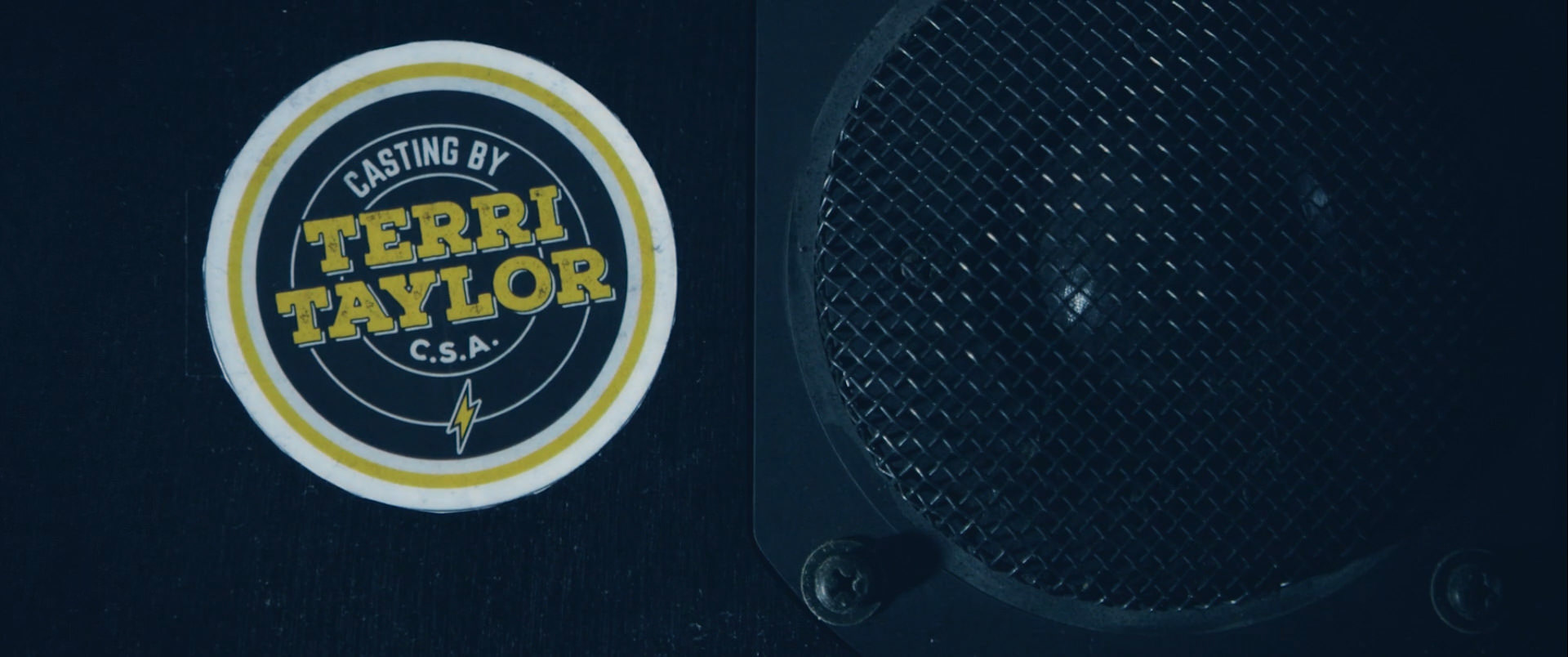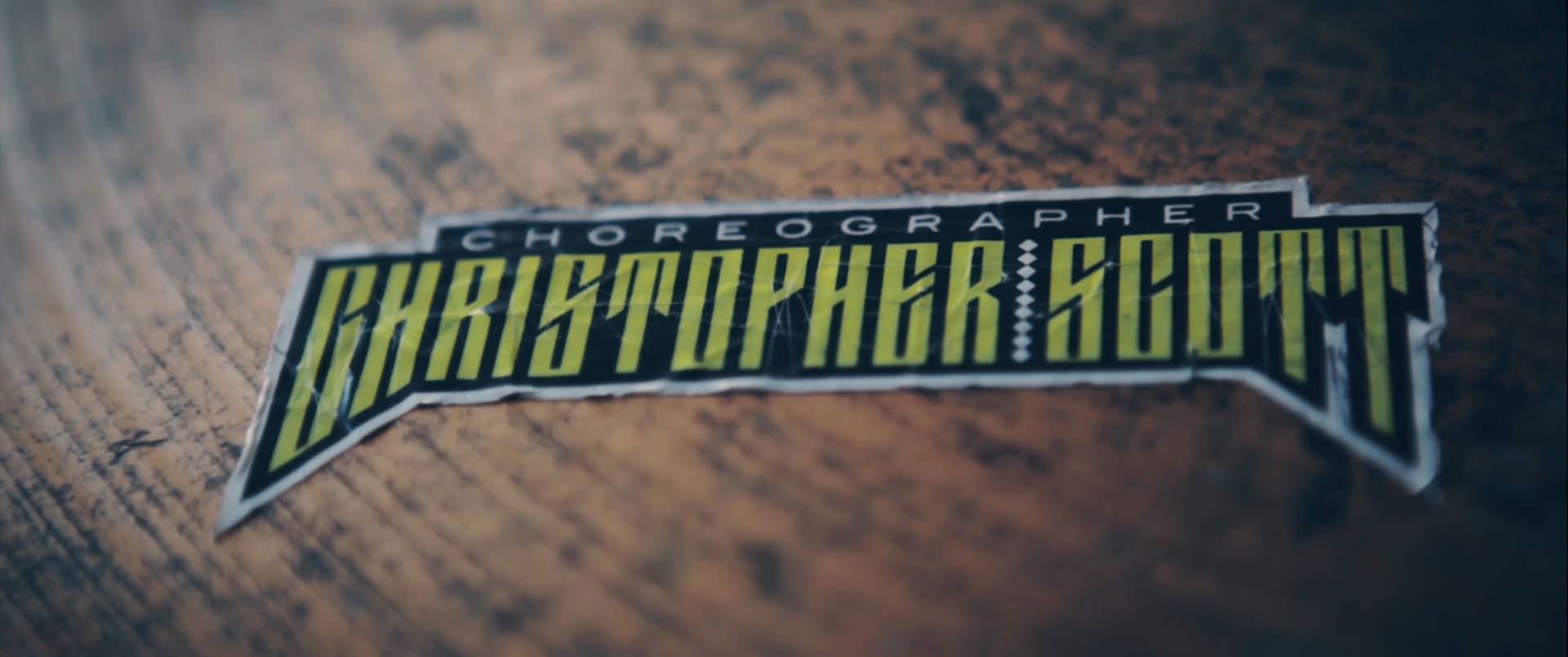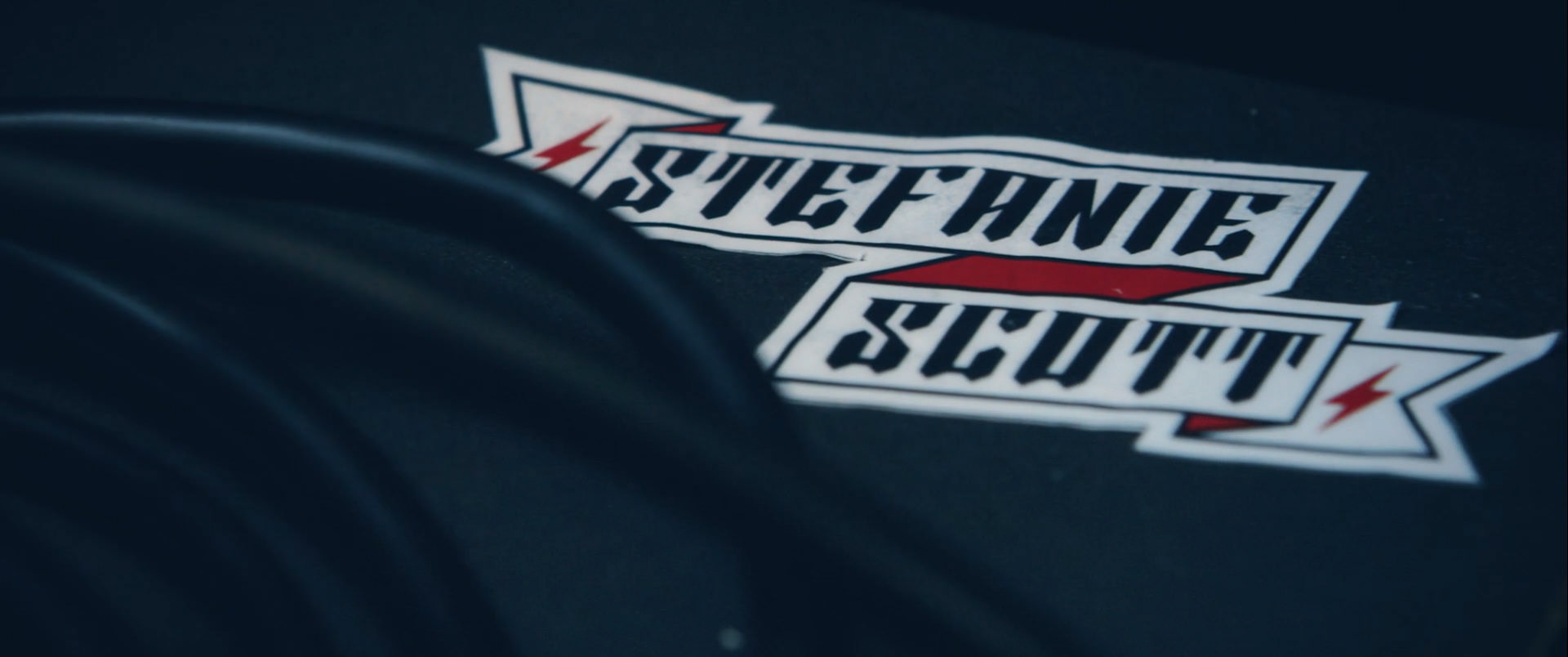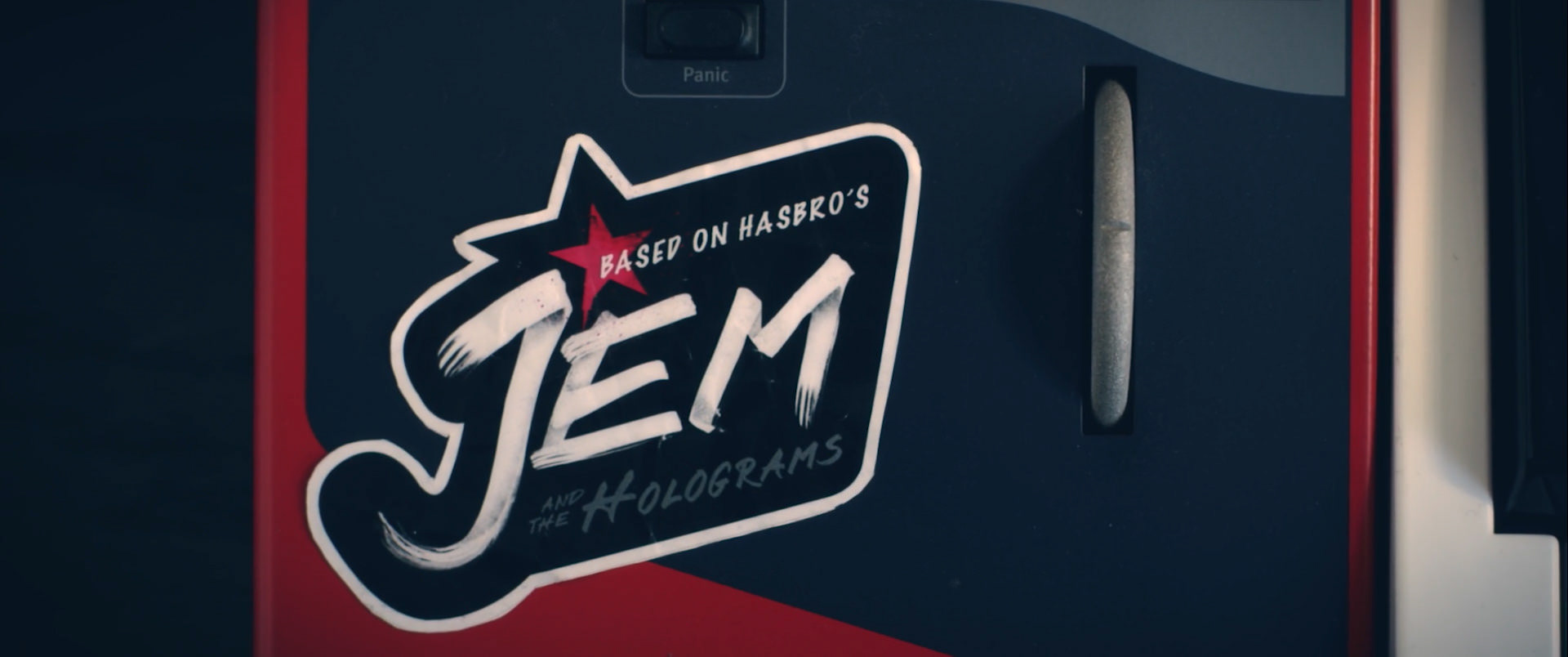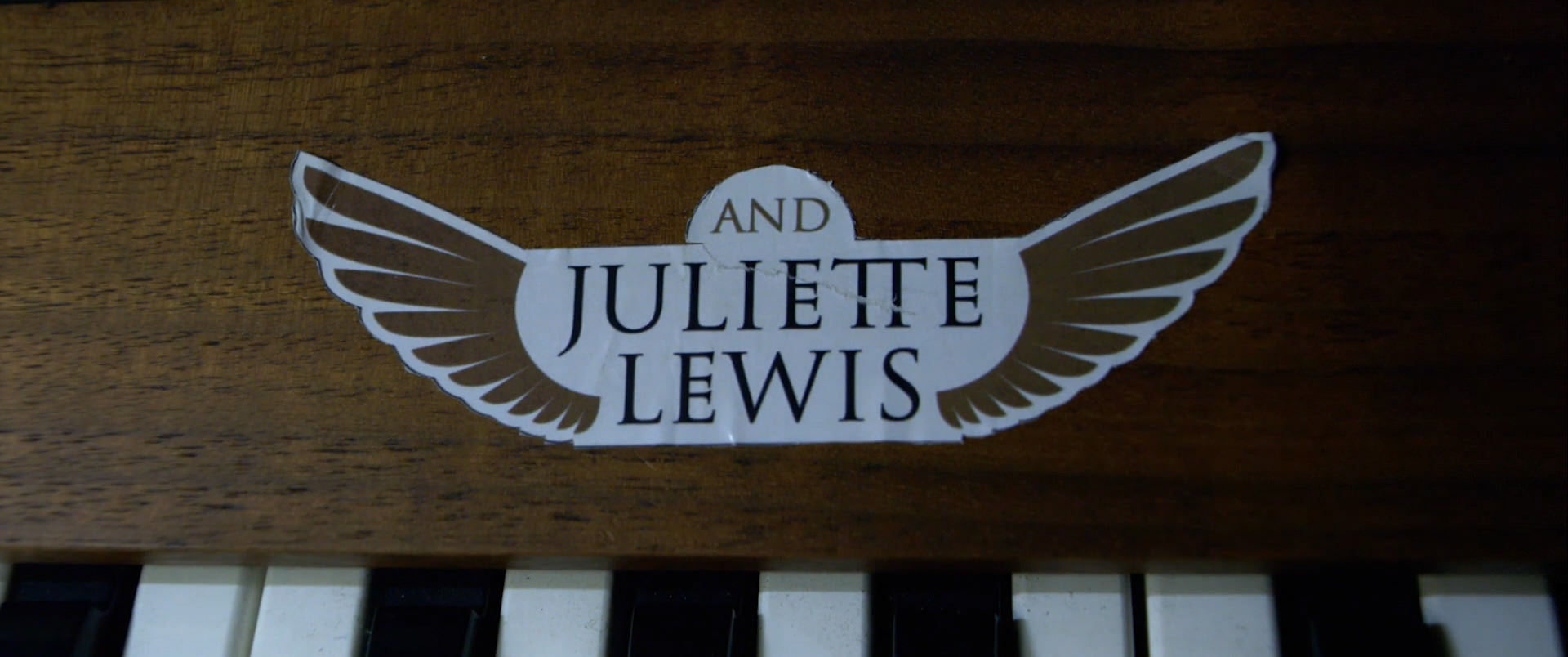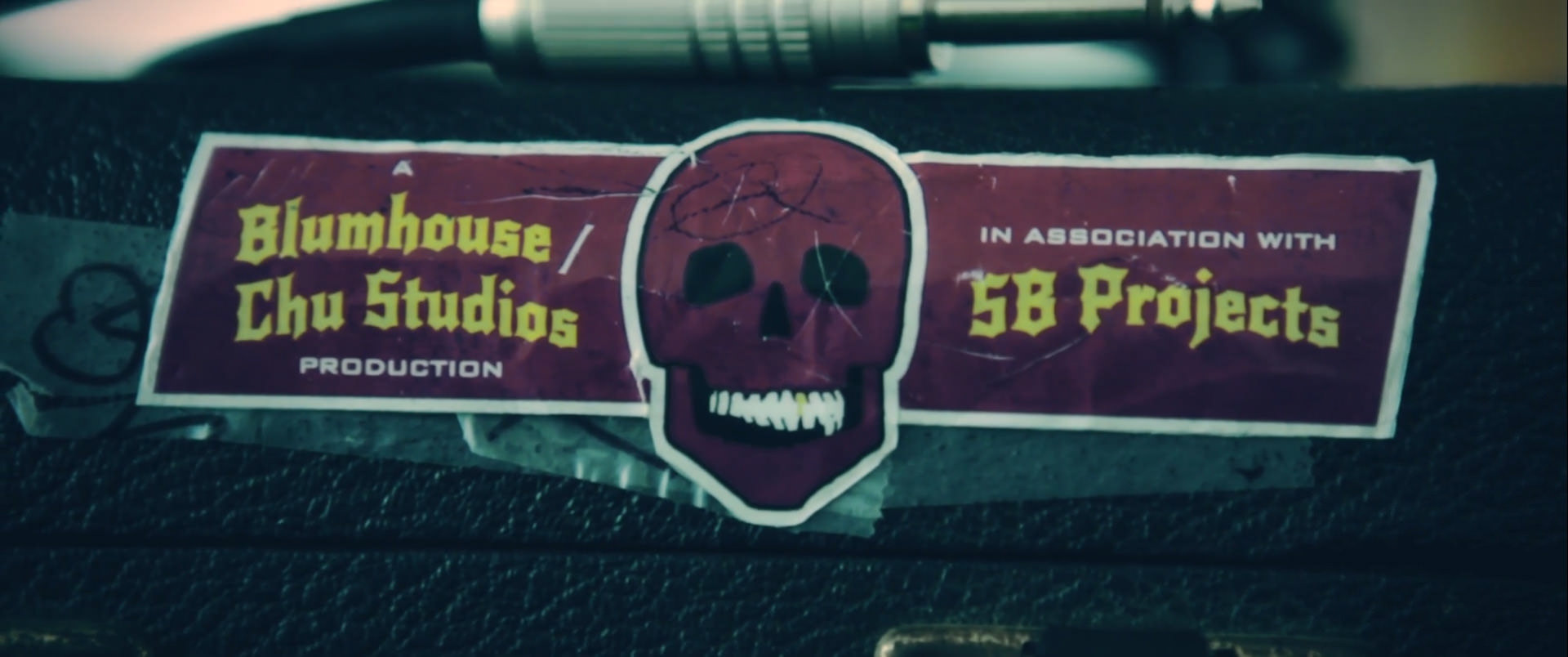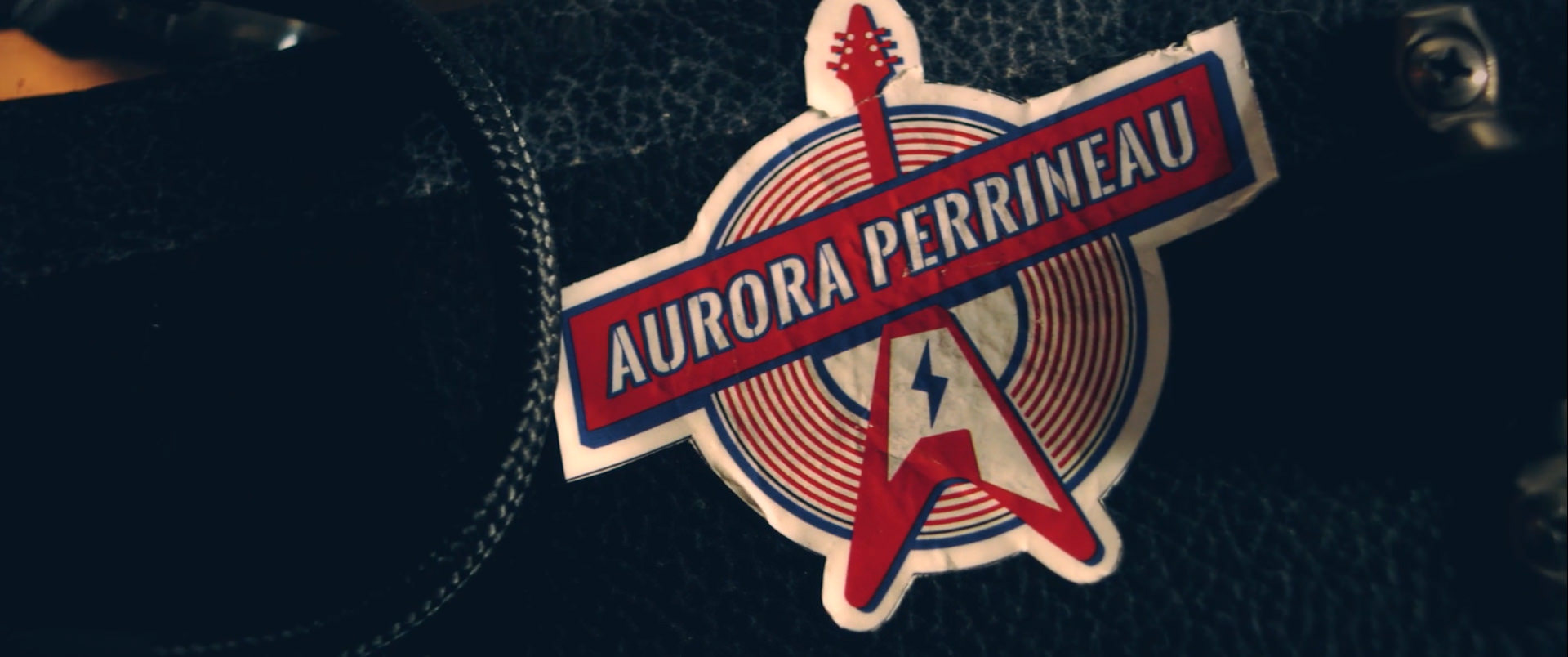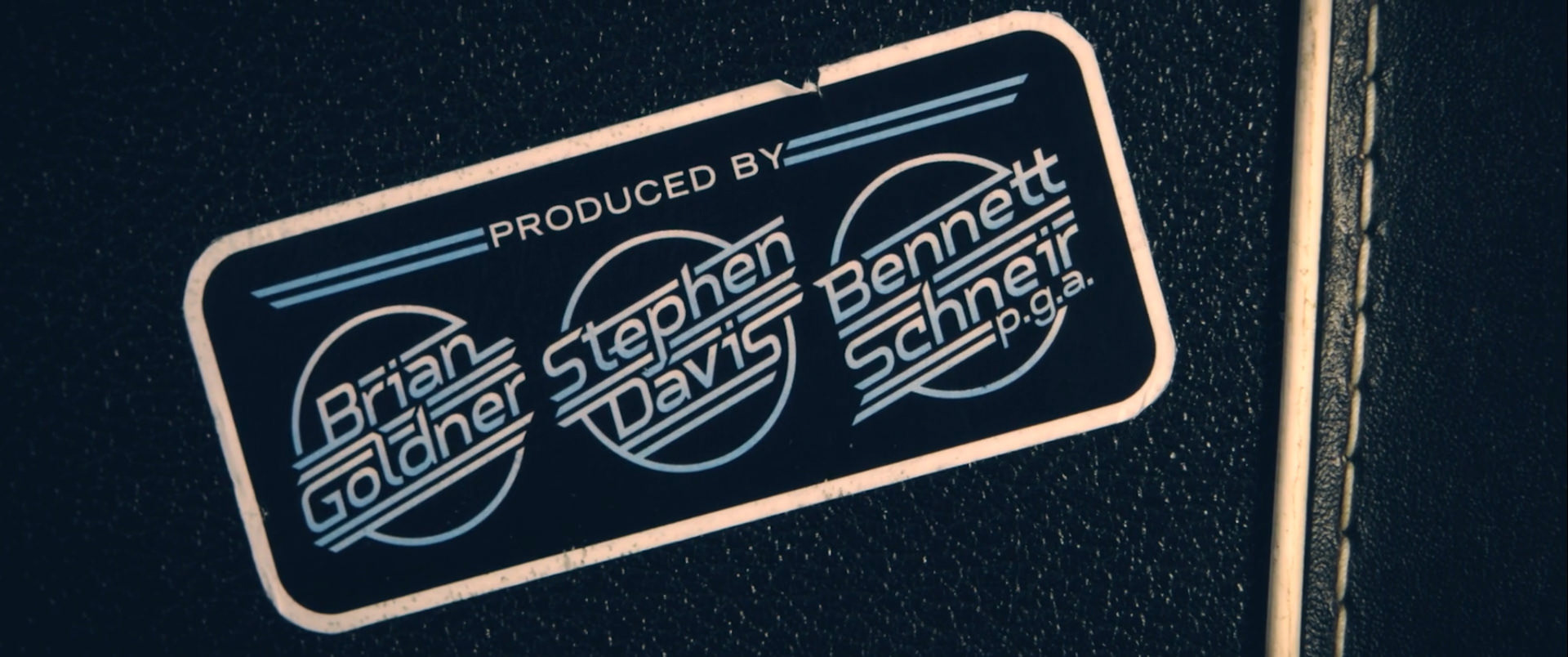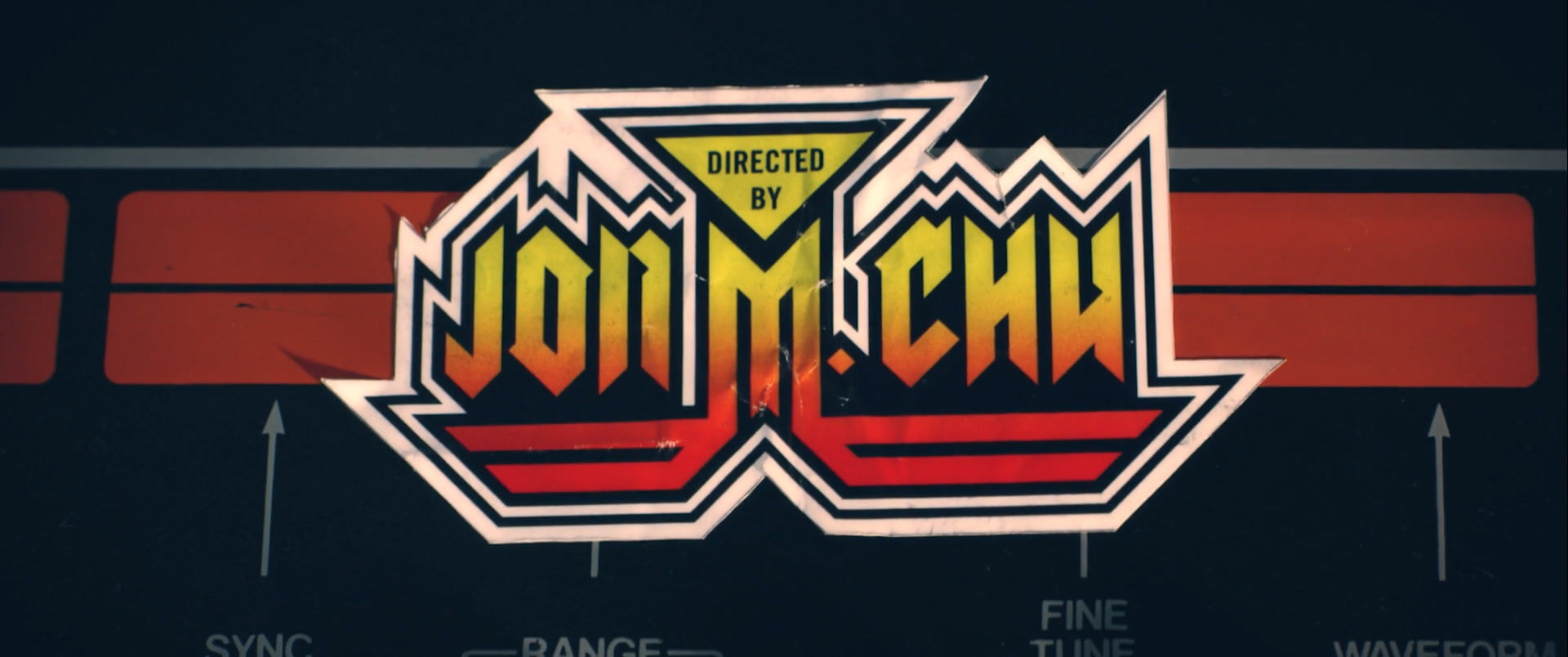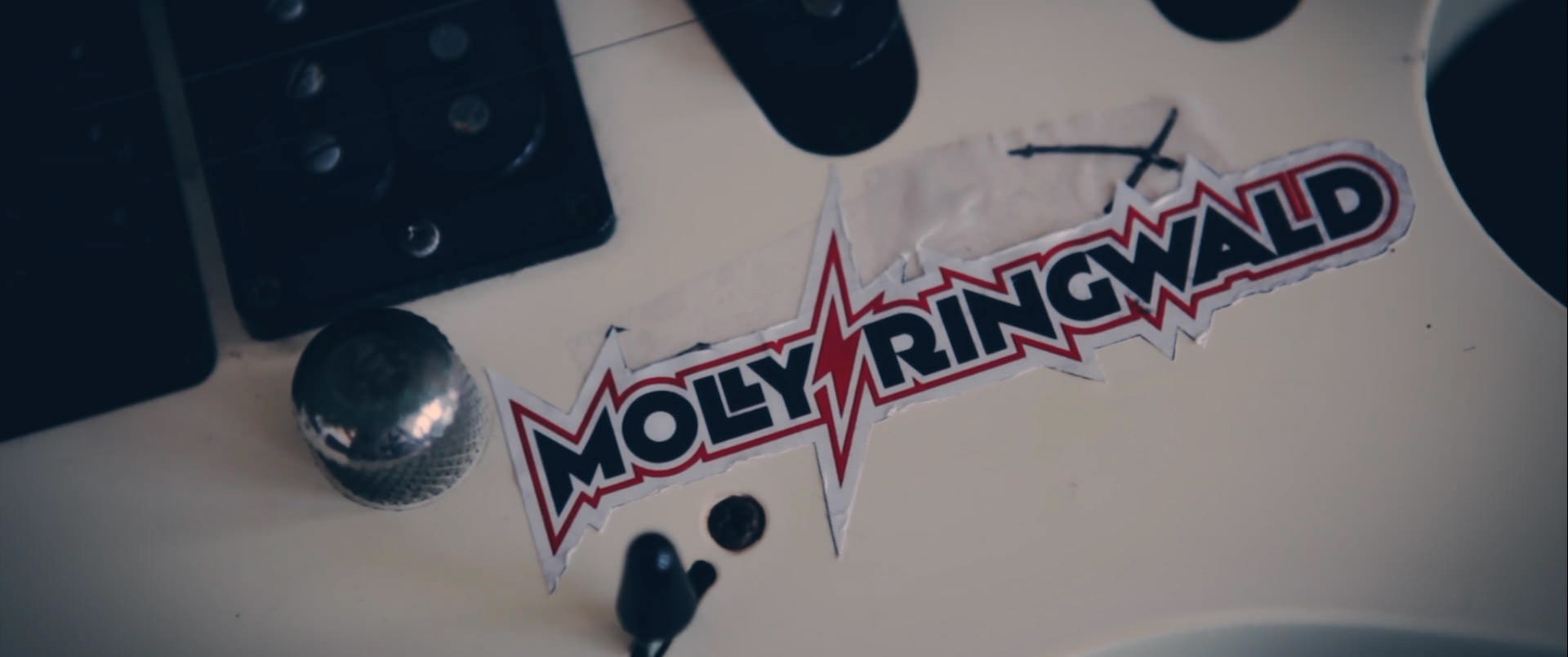
Jem and The Holograms
Custom Type Design for MOE Title Credits
Para la secuencia principal de créditos finales, diseñé un paquete de créditos basados en bandas de rock clásicas en una amplia gama de estilos, aplicando a cada nombre un diseño tipográfico personalizado y adaptando otros de fuentes existentes. Todo esto para la versión de acción real de la serie animada de los 80, Jem and the Holograms, para ser aplicado como pegatinas en el entorno musical de backstage, todo ello por encargo de Filmograph y su director creativo: Aaron Becker, con la producción de Seth Kleinberg. Ellos se encargaron del montaje, la colocación y la filmación, creando una excelente secuencia de títulos MOE.